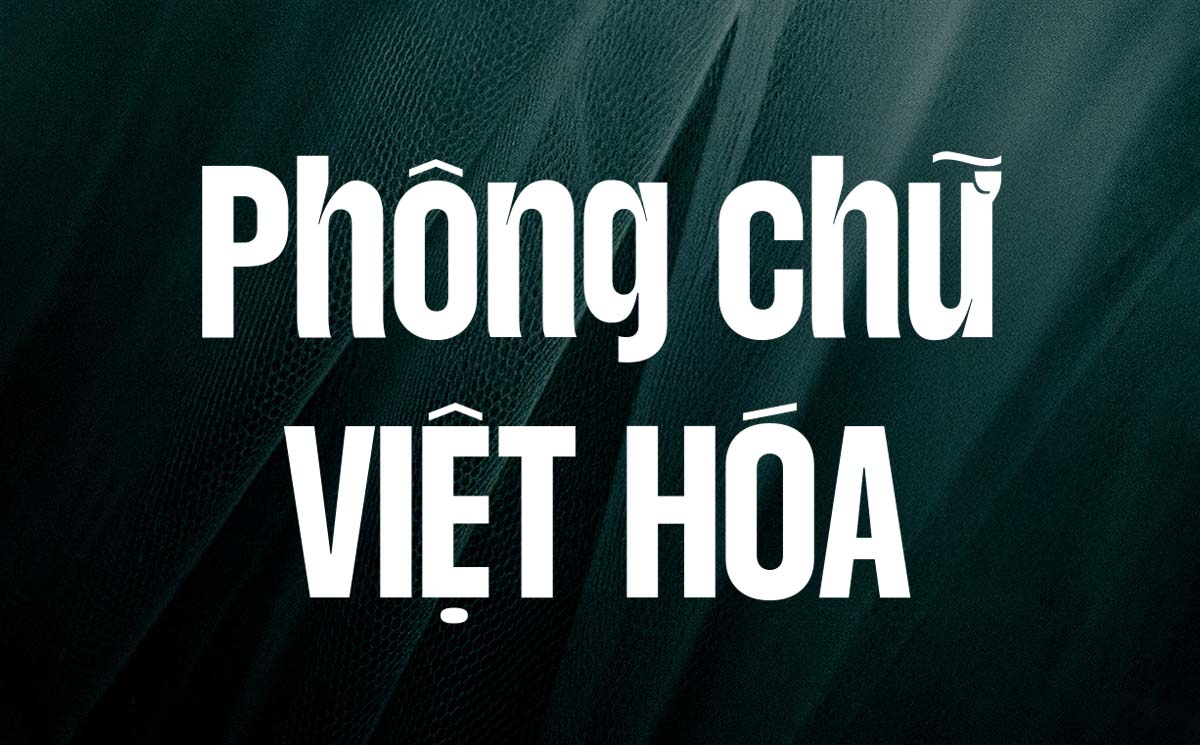
Font chữ hiện đại cứng cáp SVN-Gratelos | Font Việt hóa
Nếu bạn đang tìm kiếm một bộ font chữ mang phong cách mạnh mẽ, đột phá và chuẩn mực hiện đại để nâng tầm các dự án thiết kế đồ họa, thì SVN-Gratelos chính là sự lựa chọn hoàn hảo không thể bỏ qua. Đây là bộ font chữ hiện đại cứng cáp đã được Việt hóa hoàn chỉnh, đáp ứng tối đa nhu cầu thể hiện cá tính riêng biệt và sự chuyên nghiệp cho từng sản phẩm truyền thông. Với đường nét hình học sắc sảo, cấu trúc cân đối cùng khả năng ứng dụng đa dạng, SVN-Gratelos hứa hẹn sẽ mang đến làn gió mới ấn tượng cho bộ nhận diện thương hiệu cũng như các ấn phẩm quảng cáo của bạn.
Khám Phá Font Chữ Hiện Đại Cứng Cáp SVN-Gratelos | Bộ Font Việt Hóa Đẳng Cấp Cho Designer
Trong kỷ nguyên truyền thông thị giác phát triển vượt bậc, việc lựa chọn font chữ phù hợp đóng vai trò quyết định đến 80% sự thành công của một bản thiết kế. Font chữ hiện đại cứng cáp SVN-Gratelos ra đời nhằm giải quyết triệt để bài toán tạo điểm nhấn thị giác mạnh mẽ, thể hiện tinh thần uy nghiêm, chắc chắn và tinh tế. Bản Việt hóa chuẩn xác giúp nhà thiết kế dễ dàng truyền tải thông điệp bằng tiếng Việt một cách trọn vẹn mà không gặp bất kỳ lỗi hiển thị hay mất cân đối về mặt thẩm mỹ.
1. Đường nét hình học góc cạnh, thể hiện tinh thần hiện đại và cứng cáp
Điểm nổi bật nhất của SVN-Gratelos chính là cấu trúc nét chữ được tạo hình dựa trên các tỷ lệ hình học chuẩn mực. Các đường nét được gọt dũa vuông vức, khoẻ khoắn, hạn chế tối đa các chi tiết rườm rà để tôn lên vẻ đẹp tối giản. Phong cách sans-serif hiện đại này mang lại cảm giác vững chãi, tin cậy và vô cùng cuốn hút, đặc biệt phù hợp cho các chủ đề thuộc lĩnh vực công nghệ, thể thao, kiến trúc, thời trang nam hoặc truyền thông doanh nghiệp.
2. Bộ ký tự Việt hóa hoàn chỉnh với hệ thống dấu chuẩn thẩm mỹ
Nhiều font chữ quốc tế khi áp dụng tiếng Việt thường bị lỗi đè dấu, lệch khoảng cách hoặc các dấu thanh (sắc, huyền, hỏi, ngã, nặng) quá to làm phá vỡ tổng thể nét chữ. Đội ngũ Việt hóa đã trau chuốt bộ font Việt hóa SVN-Gratelos vô cùng tỉ mỉ. Hệ thống dấu câu và ký tự tiếng Việt đặc trưng như ê, ơ, ư, đ được thiết kế lại theo tỷ lệ vàng của font gốc, đảm bảo tính đồng nhất, hài hòa và dễ đọc trên mọi bố cục.
3. Đa dạng trọng lượng chữ (Weights), hỗ trợ phân cấp thị giác linh hoạt
Font SVN-Gratelos sở hữu hệ thống trọng lượng chữ vô cùng phong phú, từ các bản nét vừa (Regular) đến các bản siêu dày (Bold, Black). Sự đa dạng này giúp các nhà thiết kế dễ dàng xây dựng Phân cấp thị giác (Visual Hierarchy) rõ ràng cho tác phẩm của mình. Bạn có thể sử dụng nét chữ dày cho các tiêu đề chính (Headlines) cần sự chú ý tối đa và nét chữ vừa cho các đoạn văn bản phụ (Sub-headings), giúp thông điệp truyền tải đến người xem một cách tự nhiên và mạch lạc.
4. Hiệu suất hiển thị sắc nét trên cả nền tảng Kỹ thuật số và In ấn
Dù dự án của bạn là thiết kế giao diện website, ứng dụng di động, các bài đăng mạng xã hội (Facebook, Instagram, Banner Ads) hay các sản phẩm in ấn khổ lớn như Billboard, Poster, bao bì sản phẩm; SVN-Gratelos vẫn giữ nguyên được độ nét và tính rõ ràng. Nhờ cấu trúc nét chữ dầy dặn và khoảng cách chữ (kerning) được tối ưu hóa, font chữ hiển thị rất tốt ngay cả khi thu nhỏ trên màn hình điện thoại hoặc khi in nổi trên các chất liệu cao cấp.
5. Khả năng kết hợp font chữ (Font Pairing) vô cùng linh hoạt
Nhờ mang tinh thần trung tính, hiện đại và cứng cáp, SVN-Gratelos có khả năng bắt cặp hoàn hảo với nhiều dòng font khác nhau. Bạn có thể kết hợp tiêu đề SVN-Gratelos cứng cáp với một dòng font Serif cổ điển lịch lãm hoặc một font Script mềm mại để tạo nên hiệu ứng tương phản đầy tính nghệ thuật. Sự linh hoạt này giúp tiết kiệm thời gian thử nghiệm font và mở rộng không gian sáng tạo cho các designer.</p>
Ứng Dụng Thực Tế Của Font Việt Hóa SVN-Gratelos Trong Thiết Kế Đồ Họa
Sở hữu diện mạo đột phá và cá tính mạnh mẽ, bộ font chữ hiện đại cứng cáp SVN-Gratelos được sử dụng rộng rãi trong nhiều lĩnh vực sáng tạo khác nhau:
• Thiết kế Logo & Nhận diện thương hiệu: Thích hợp cho các công ty công nghệ, bất động sản, thương hiệu thời trang street-style, phòng gym, hoặc các tập đoàn tài chính cần khẳng định sự uy tín và bền vững.
• Ấn phẩm quảng cáo & Truyền thông: Tạo sức hút tức thì trên các Poster sự kiện, Banner chạy quảng cáo, Thumbnail YouTube, Bìa sách hoặc Bìa album ca nhạc.
• Bao bì & Nhãn mác sản phẩm: Đem lại vẻ ngoài sang trọng, hiện đại cho các sản phẩm dành cho nam giới, nước hoa, đồ uống năng lượng hoặc thiết bị công nghệ hi-tech.
• Giao diện UI/UX Website & App: Dùng làm tiêu đề nổi bật thu hút ánh nhìn người dùng ngay từ những giây đầu tiên truy cập Landing Page.
Tại Sao Bạn Nên Chọn Font SVN-Gratelos Cho Các Dự Án Sáng Tạo?
Việc đầu tư chọn lựa một bộ font chất lượng như SVN-Gratelos mang lại nhiều lợi ích vượt trội cho công việc thiết kế chuyên nghiệp:
1. Tối ưu thời gian làm việc: Font chữ đã được Việt hóa sẵn sàng, không tốn thời gian căn chỉnh dấu hay sửa lỗi gõ tiếng Việt.
2. Tăng tính chuyên nghiệp cho sản phẩm: Nét chữ hình học hiện đại giúp sản phẩm thiết kế trông bắt mắt, thời thượng và tiếp cận đúng đối tượng khách hàng mục tiêu.